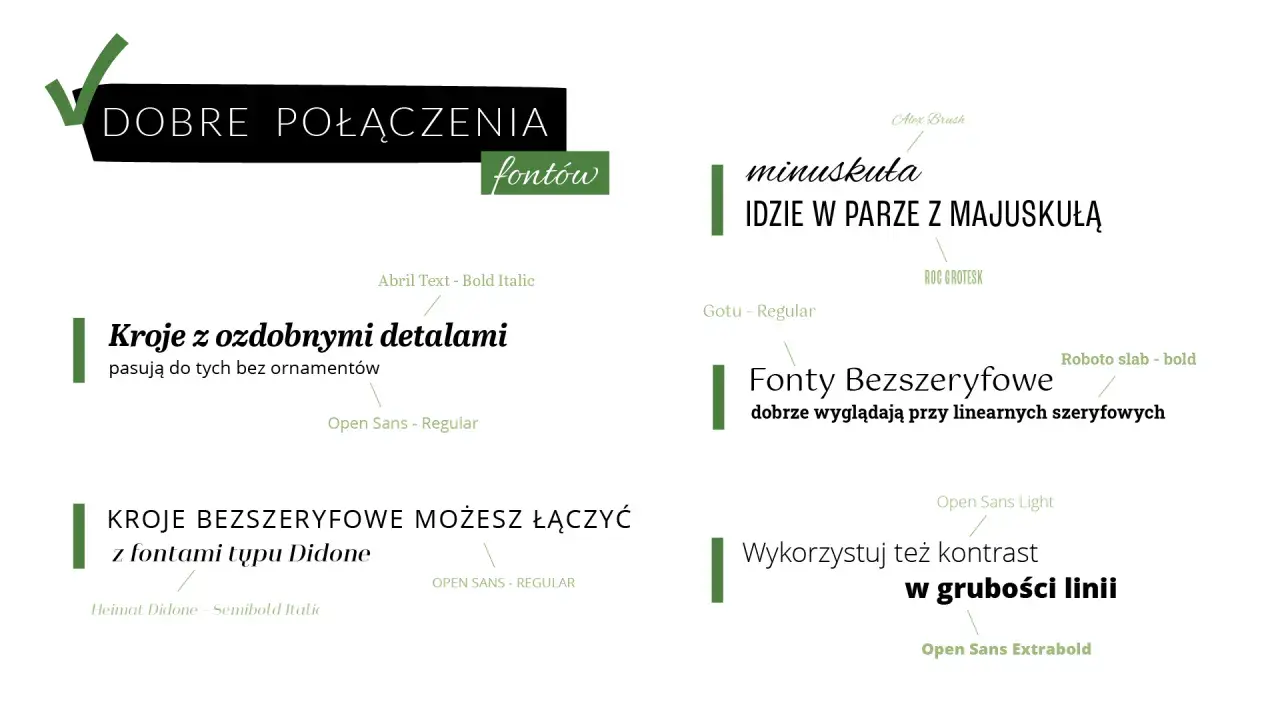
Dobrze dobrana typografia decyduje o tym, czy treść czyta się płynnie, czy tylko przewija wzrokiem. W praktyce czcionki tekstu wpływają na wygodę czytania, odbiór marki i skuteczność strony w e-commerce oraz SEO. W tym tekście pokazuję, jak odróżnić krój pisma od fontu, jak dobrać rodzinę do treści i medium oraz które parametry naprawdę robią różnicę.
Najważniejsze decyzje typograficzne zapadają szybciej, niż myślisz
- Najpierw wybieram medium: ekran, druk albo oba naraz, bo każdy z nich premiuje inny krój.
- Do długiego tekstu stawiam na prosty, czytelny font, a ozdobne rozwiązania zostawiam na nagłówki i akcenty.
- Rozmiar, interlinia, długość wiersza i kontrast mają większy wpływ na czytelność niż sam „modny” wygląd pisma.
- Na stronie internetowej liczy się także szybkość ładowania i stabilność układu, więc font nie może psuć UX.
- W praktyce najlepiej działają projekty, które mają jedną wyraźną hierarchię i mało przypadkowych odmian.
Czym różni się krój pisma od czcionki i dlaczego to ważne
W codziennej rozmowie te pojęcia często się mieszają, ale w pracy nad tekstem dobrze jest je rozdzielić. Krój pisma to wygląd liter, font to cyfrowy zapis tego kroju, a czcionka historycznie oznaczała pojedynczy element składu. W praktyce projektowej patrzę jednak przede wszystkim na to, jak litery zachowują się w zdaniu, w akapicie i na ekranie telefonu.
- Krój pisma opisuje styl liter: proporcje, zakończenia, rytm i charakter.
- Font to plik, który pozwala ten krój wyświetlić w systemie albo w przeglądarce.
- Odmiana to np. Regular, Italic, Bold czy SemiBold.
- Stopień pisma to rozmiar tekstu, czyli to, czy akapit ma 14, 16 czy 18 px.
Jeśli te pojęcia są uporządkowane, łatwiej dobrać rozwiązanie do zadania, zamiast wybierać font wyłącznie dlatego, że „ładnie wygląda”. Ja zwykle zaczynam od pytania, czy tekst ma informować, sprzedawać, budować klimat czy prowadzić przez interfejs. Kiedy to wiadomo, można sensownie dobrać rodzinę do medium, a nie do chwilowej mody.
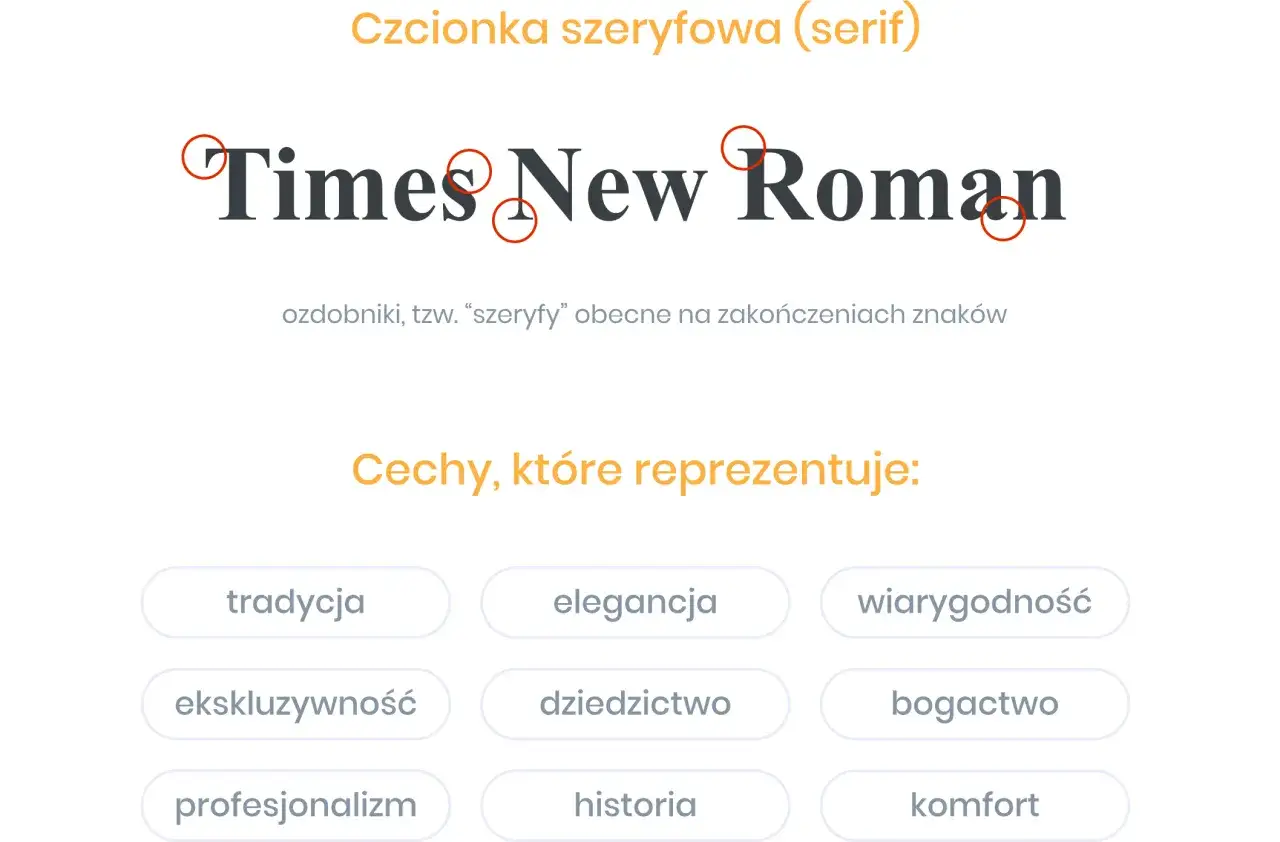
Jak dobrać krój do treści, marki i medium
Ja zwykle patrzę na font w trzech warstwach: co ma robić tekst, gdzie ma się pojawić i jaki charakter ma mieć marka. Inny krój sprawdzi się w artykule eksperckim, inny w sklepie internetowym, a jeszcze inny w pliku PDF czy katalogu drukowanym.
| Rodzaj kroju | Gdzie działa najlepiej | Co zyskujesz | Na co uważać |
|---|---|---|---|
| Szeryfowy | Dłuższe teksty redakcyjne, raporty, edytoriale, druk | Spokojniejszy rytm czytania i bardziej klasyczny charakter | W małych rozmiarach i na słabszych ekranach może tracić ostrość |
| Bezszeryfowy | Strony WWW, aplikacje, mobile, e-commerce, UI | Wyraźną czytelność i prosty odbiór na ekranie | Bez dobrego układu może wyglądać zbyt neutralnie |
| Monospace | Kod, dane techniczne, tabele, fragmenty diagnostyczne | Równy rytm znaków i łatwiejsze porównywanie informacji | Nie nadaje się do długich akapitów |
| Displayowy | Nagłówki, hero, kampanie, logotypy | Mocny charakter i wyraźny akcent wizualny | W treści ciągłej szybko męczy wzrok |
Jeśli mam wybrać tylko jedną zasadę, to biorę tę: tekstu ciągłego nie projektuje się jak plakatu. Dekoracyjny krój może zrobić świetne pierwsze wrażenie, ale po kilku akapitach zwykle zaczyna przeszkadzać. Z tego powodu do treści podstawowej najczęściej wygrywa prosty sans-serif albo dobrze zaprojektowany szeryf, a display zostaje w nagłówku. Żeby to działało naprawdę dobrze, trzeba jeszcze ustawić właściwe proporcje.
Parametry, które naprawdę decydują o czytelności
W typografii największą różnicę robią rzeczy, które na pierwszy rzut oka wydają się drugorzędne. Ja zawsze sprawdzam wielkość, interlinię, długość wiersza, grubość znaków i kontrast, bo to one decydują o tym, czy tekst „płynie”.
| Element | Sensowny zakres na web | W druku | Dlaczego to działa |
|---|---|---|---|
| Tekst podstawowy | 16-18 px | 9-11 pt w książkach i raportach, 11-12 pt w materiałach marketingowych | Ułatwia czytanie bez zmuszania użytkownika do powiększania |
| Interlinia | 1.5-1.7 | 1.2-1.4 lub 120-140% | Oddziela wiersze i poprawia rytm akapitu |
| Długość wiersza | 45-75 znaków | 45-70 znaków | Zmniejsza zmęczenie wzroku i ułatwia śledzenie linii |
| Liczba rodzin fontów | 1-2 | 1-2 | Chroni hierarchię i porządek wizualny |
| Kontrast | Minimum 4.5:1 dla normalnego tekstu | Wyraźny, bez „szarego na szarym” | Zwiększa dostępność i poprawia komfort czytania |
| Odmiany grubości | 2-3 wystarczą w większości projektów | 2-3 wystarczą w większości projektów | Buduje hierarchię bez chaosu |
Jeśli krój ma wysoki x-height, czyli dużą wysokość małych liter, mały tekst zwykle wygląda czyściej. To jeden z powodów, dla których w projektach internetowych często wygrywają proste, otwarte kroje zamiast eleganckich, cienkich wariantów. Z kolei w druku można pozwolić sobie na odrobinę więcej subtelności, bo papier nie walczy z rozdzielczością ekranu. Nawet dobry zestaw parametrów nie pomoże jednak wtedy, gdy po drodze pojawią się klasyczne błędy.
- Czy długość wiersza nie rozlewa akapitów na całą szerokość strony.
- Czy wygląd nie psuje się po przełączeniu z webfontu na font systemowy.
Jeśli ten audyt przechodzi bez zgrzytów, typografia zaczyna pracować na treść, a nie przeciwko niej. Z mojego doświadczenia wynika, że lepszy efekt daje spokojny, konsekwentny układ niż efektowny krój, który po kilku minutach męczy wzrok i rozprasza uwagę. Właśnie dlatego przy projektowaniu stron, artykułów i materiałów sprzedażowych najpierw dopracowuję czytelność, a dopiero potem dokładam charakter marki.